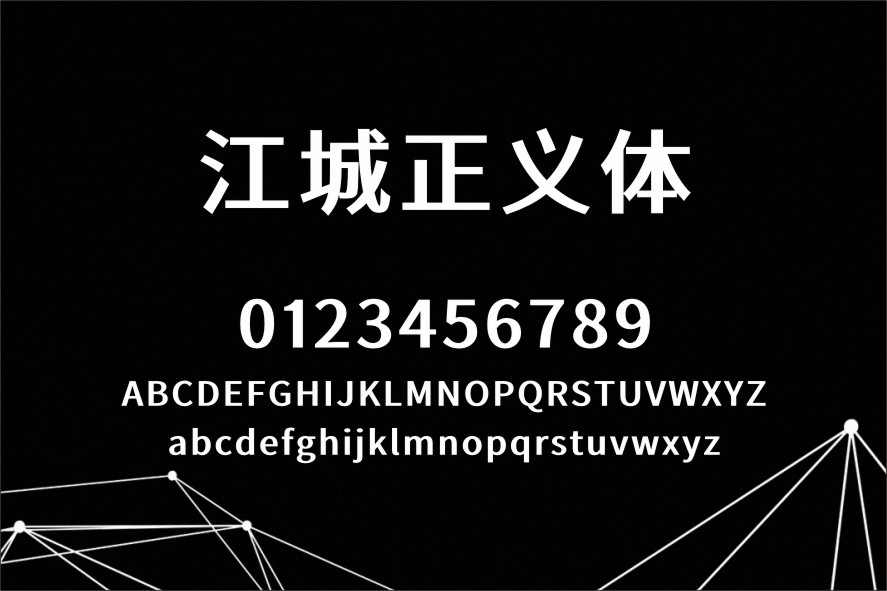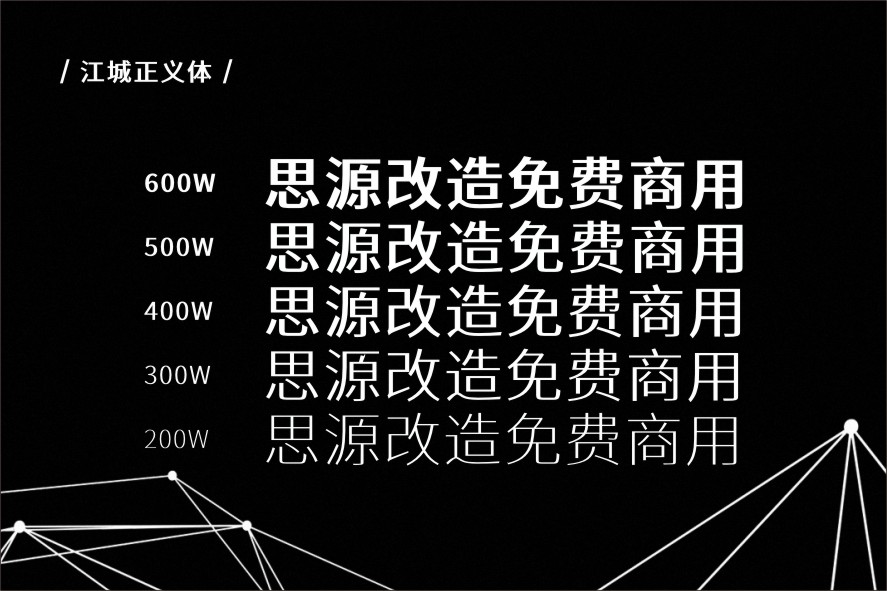
江城正义体是由国内字体爱好者刘鹏(@设裂星辰)基于思源黑体改造的一款免费可商用中文字体。与日本设计师发布的源暎漫画体有点类似,不同的是源暎漫画体是基于日本版思源黑体改造,只有一个字重且对简体中文支持不是很友好。而江城正义体是基于中国版思源黑体改造,更符合中国大陆的习惯,且有5个字重(200W、300W、400W、500W、600W)可供选择。
江城正义体把思源黑体的笔画做了横向调细,纵向增粗的处理,撇、捺等笔画从落笔到收笔逐渐变细,使整个字体呈现“横细竖粗”,看起来有点粗宋的风格。而且简繁体基本都不缺字( 6763 个简体中文字符和 6865 个繁体中文字符),再加上丰富的字重,不管是海报、LOGO设计,还是杂志、书籍等印刷品的正文或标题都能适用。
- 轻量(200W-300W):适合正文辅助、小标题
- 常规(400W):通用标题
- 粗重(500W-600W):主标题、品牌标志